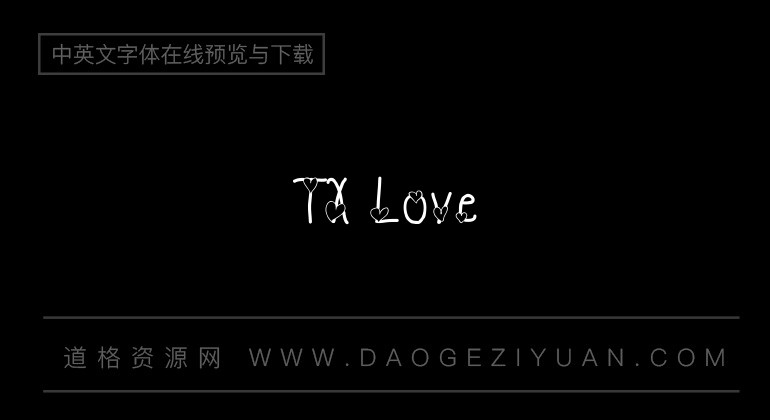
TX Love
TX Love是由著名的英国设计师Timothy Donaldson设计的一款字体。它是一种英式手写体,具有温柔、细腻、活泼的特点,让人一看就能感受到它的温暖和柔美。它有着清晰的线条,温柔的曲线,给人一种温馨、柔和的感觉。它适用于各种报纸、杂志、海报、书籍、礼品卡等,可以提供一种更加精致、温柔的体验。
TX Love是一款非常不错的手写艺术字体,具有很好的视觉感,适合于文化类的宣传设计、商业类品牌的广告和产品包装设计以及个性化文字排版等较多场景。